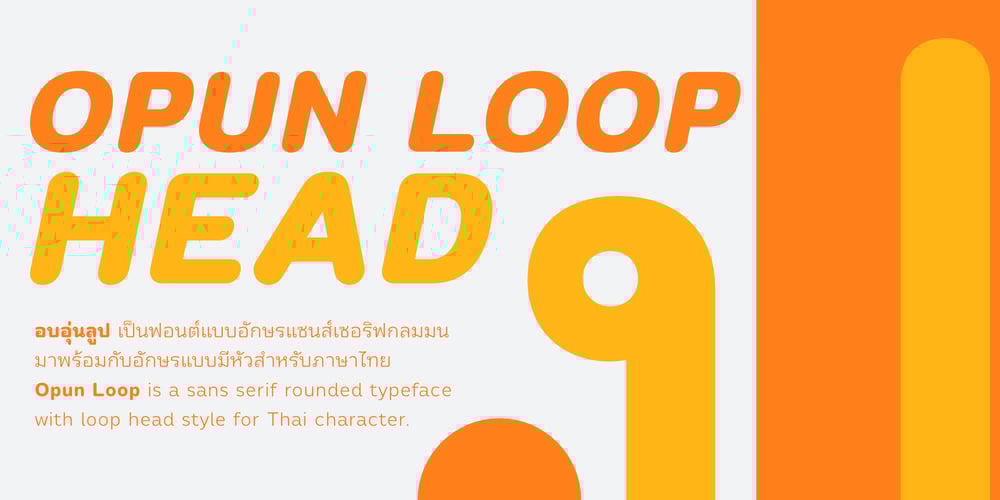
Opun Loop Font Family was designed by Anupap Jaichumnan and published by Jipatype. Opun Loop contains 18 styles and family package options. อบอุ่นลูป เป็นอักษรแบบแซนส์เซอริฟกลมมน มาพร้อมกับอักษรแบบมีหัวสำหรับภาษาไทย ดูกึงทางการ อ่อนโยน น่ารัก ใช้สำหรับเป็นพาดหัวก็ดี หรือเป็นเนื้อความก็เหมาะสม มีทั้งหมด 9 น้ำหนักและตัวเอียงของแต่ละน้ำหนักรวมทั้งหมดมี 18 สไตล์ และมีฟีเจอร์อื่น ๆ อาทิเช่น Small Caps และฟีเจอร์อื่น ๆ พร้อมให้คุณได้เลือกใช้งาน รองรับหลากหลายภาษาOpun Loop is a sans serif rounded typeface with loop head style for Thai character. Semi-formal, Softly, Lovely feel. Suitable for headline and text body. Comes with 9 weights and italics of each weight total 18 styles, and there are features such as Small Caps and many features available for you. Support multi-languages.